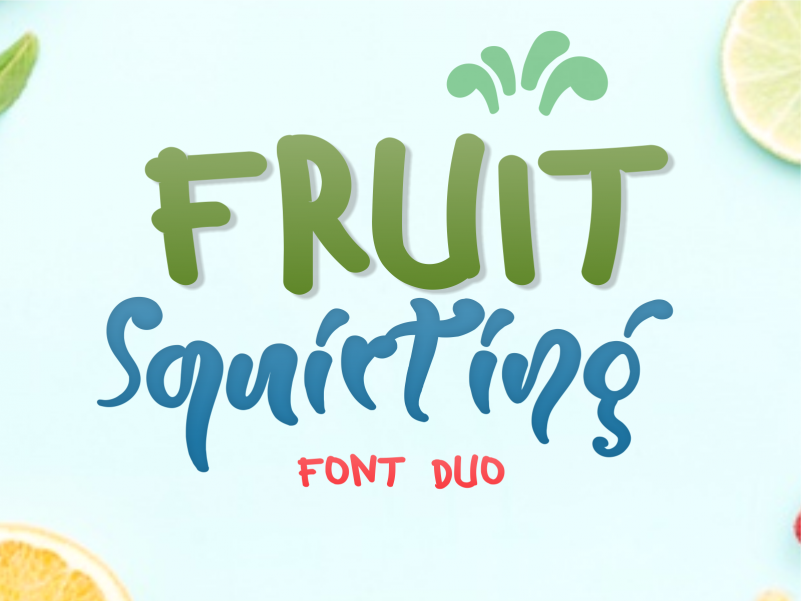
Esta fonte é a escolha perfeita para aqueles que buscam sofisticação e elegância em cada letra. Com seu estilo refinado e alternativas modernas, ela se destaca como a fonte ideal para qualquer projeto. Fruit Squirting é uma fonte de display PUA codificada, permitindo uma facilidade total na manipulação de todos os gílitos e swashes. Para designers que procuram um visual fresco e único, esta font traz elementos coloridos e estilizados que complementam perfeitamente qualquer projeto. É a escolha ideal para adicionar um toque especial às suas criações digitais, seja em posters de moda, designs gráficos ou até mesmo em conteúdo digital para redes sociais. Nuryanto Dwi é o designer por trás desta fonte única e elegante, que oferece aos usuários a facilidade de usá-la nos seus projetos. Seja você um profissional da área ou apenas um criador de designs amador, Fruit Squirting será uma escolha segura para aqueles procurando algo único em sua paleta de fontes.